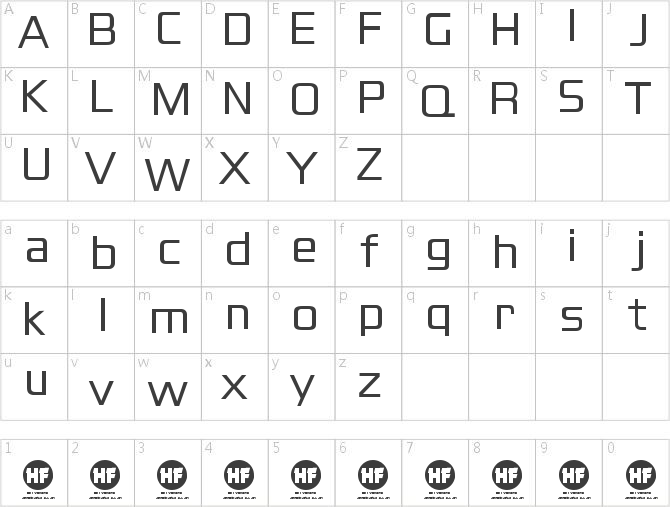
blackthorns-regular DEMO 詳情頁(yè)
blackthorns-regular DEMO字體字庫(kù)是一款讓人賞心悅目、百看不厭的英文字體,適合各類廣告和產(chǎn)品包裝設(shè)計(jì)應(yīng)用,字體大小0.1MB,格式為ttf字體,上傳用戶是shiqiuping,作者/版權(quán)方為未知